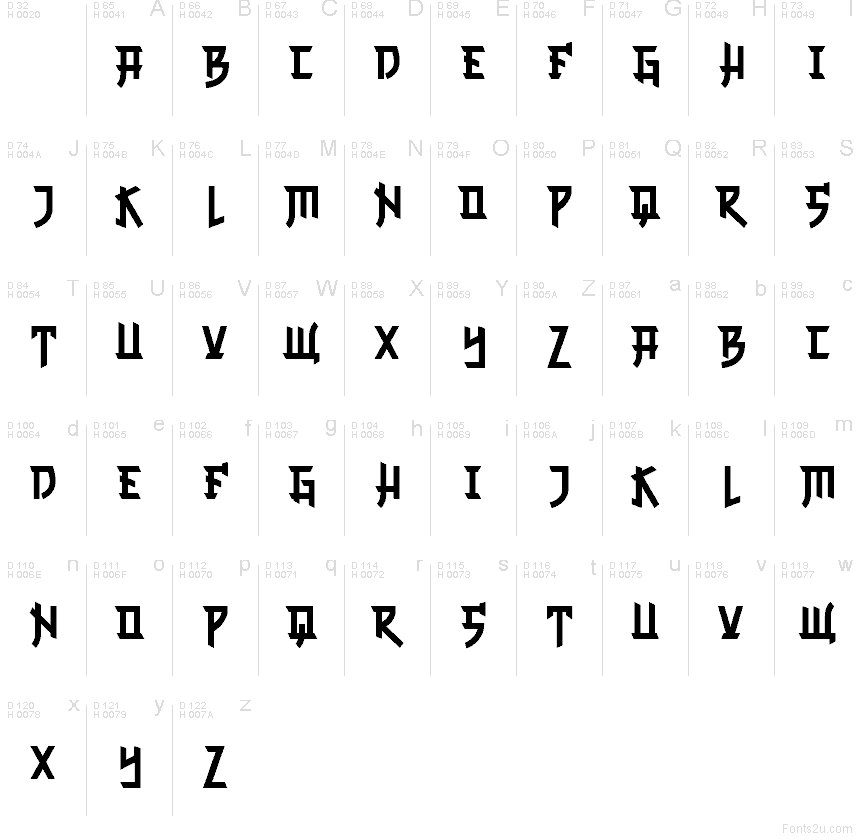
Chinese Karaoke, de Vladimir Nikolic, es una tipografía display gratuita con un estilo inspirado en la caligrafía asiática y mayúsculas nítidas, ideales para cartelería. Sus letras combinan un peso contundente con esquinas en forma de gancho, diagonales recortadas y remates puntiagudos que recuerdan a los letreros de Chinatown y los menús de comida para llevar, sin llegar a ser excesivamente ornamentales.
Esto convierte a esta fuente gratuita en una opción natural para branding de restaurantes, carteles de comida callejera, folletos de eventos, títulos de juegos retro y cabeceras que necesiten un toque asiático al instante. También funciona para titulares cortos y monogramas, donde esos ángulos marcados y puntos colgantes le dan incluso a unas pocas letras una silueta estilizada y llamativa.